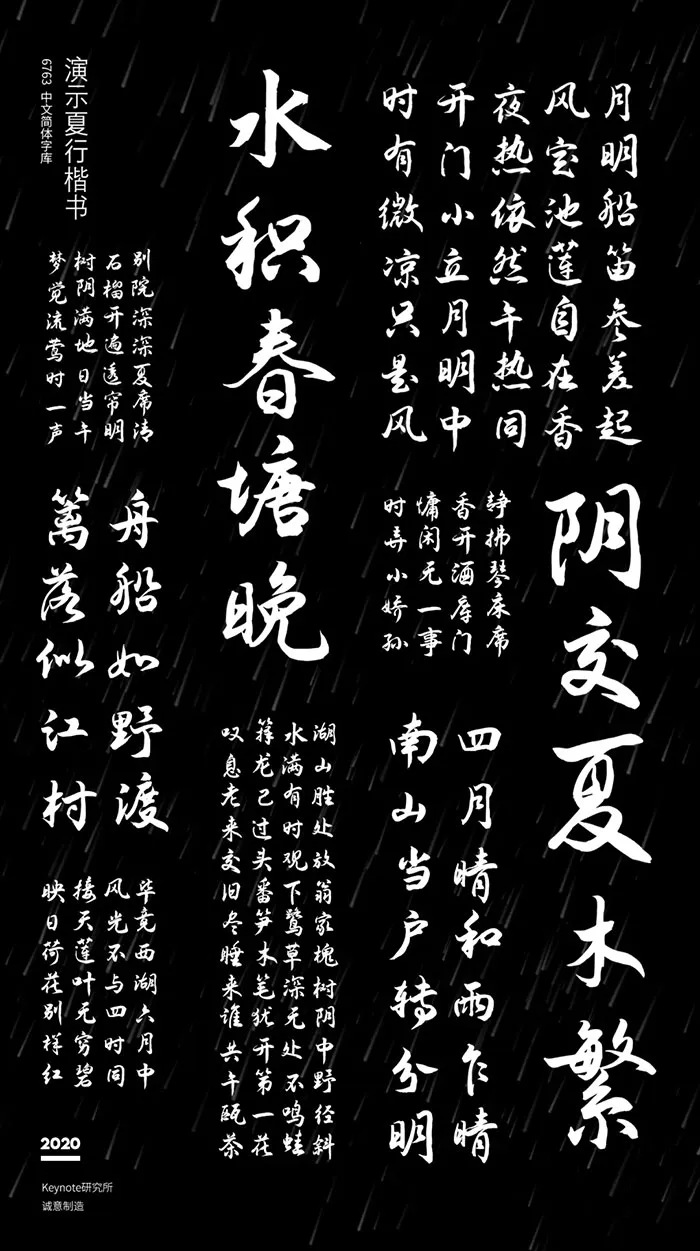
你好,這裡是 Keynote研究所,我是人生哥。設計,重要的是,如何解決用戶所面臨的當前問題,兩年前,為了解決在 Keynote 中文字不能傾斜的問題,我做了一次大膽的嘗試:自己動手改造出一款 Keynote 可用的傾斜字,讓幻燈片設計師可以在Keynote中一鍵傾斜文字。於是基於對谷歌開源字體「思源黑體」的傾斜處理,便有了 — 演示斜黑體。但很多人說,這款字應該叫做 演示斜槓體,因為是它,讓關於我的故事不再是隻有PPT,又加上了一道斜槓——字體。
今年3月,我發佈了兩款免費可商用手寫字體,演示佛系體 和 演示悠然小楷 分別來自紀國才老先生和孟祥媛同學的手寫字稿。得益於在做字技術上的突破,從字稿到字體的封包效率幾乎越來越快,已經可以實現3天內結束字體封包。今天我將再次發佈三款免費可商用字體,全部為半自動流程製作,當然我也已經做好了被某些人罵的準備,似乎一切手寫字體都天生具備這種基因,所以,請讓你們的狂風暴雨來的更猛烈一些吧!這三款字分別為:演示春風楷、演示夏行楷、演示秋鴻楷,源於演示,也不止於演示。
演示夏行楷,,字稿作者:劉錫棟,中國灕江書畫藝術家協會理事丨北京中國書畫研究院研究員丨中國民族硬筆書法家協會會員丨中國楹聯學會會員丨黑龍江楹聯家協會會員丨高級政工師,已退休,字體制作:人生哥(和他的半自動電腦)